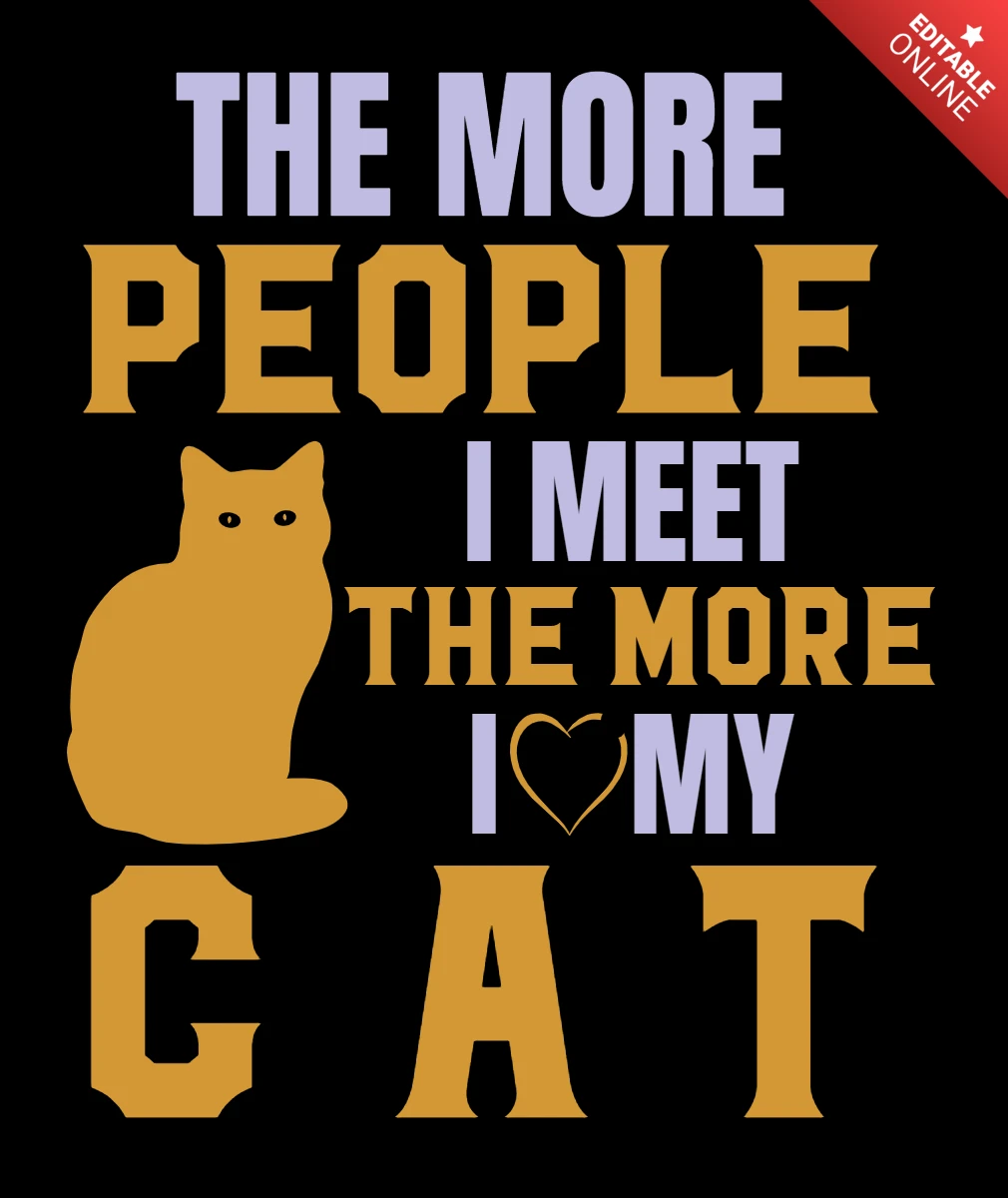
Modèle de typographie de l'amour du chat enjoué
Éditer dans Design Studio Télécharger en JPGLibérez votre créativité avec notre modèle de design vibrant sur le thème des chats, parfait pour un merchandising de vêtements audacieux qui met en avant votre amour pour les chats de manière ludique et humoristique !